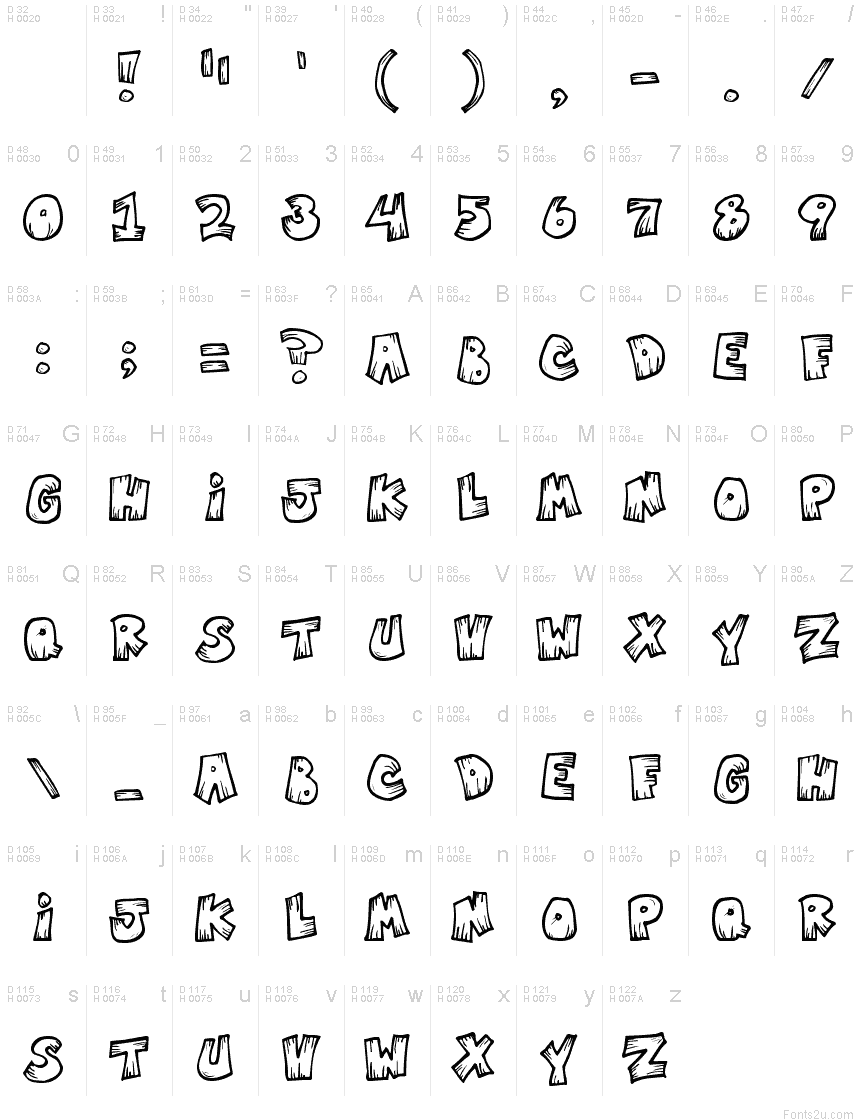
Mister Vampire è un font cartoon gratuito caratterizzato da lettere ruvide disegnate a mano e contorni irregolari che gli conferiscono un aspetto graffiato e spettrale. Le forme oscillano leggermente da un carattere all'altro, con tagli inclinati e segni interni liberi che rendono l'insieme simile a un disegno veloce realizzato con un pennarello.
Mister Vampire funziona benissimo per poster di Halloween, inviti a tema mostri, titoli di fumetti, volantini per feste di bambini e insegne di negozi di costumi, perché la sua forma irregolare mantiene il tono vivace senza diventare troppo serio. Questo font gratuito è adatto anche per etichette horror, grafiche per eventi e brevi frasi decorative in cui lo stile fatto a mano riesce a trasmettere il tema da solo.